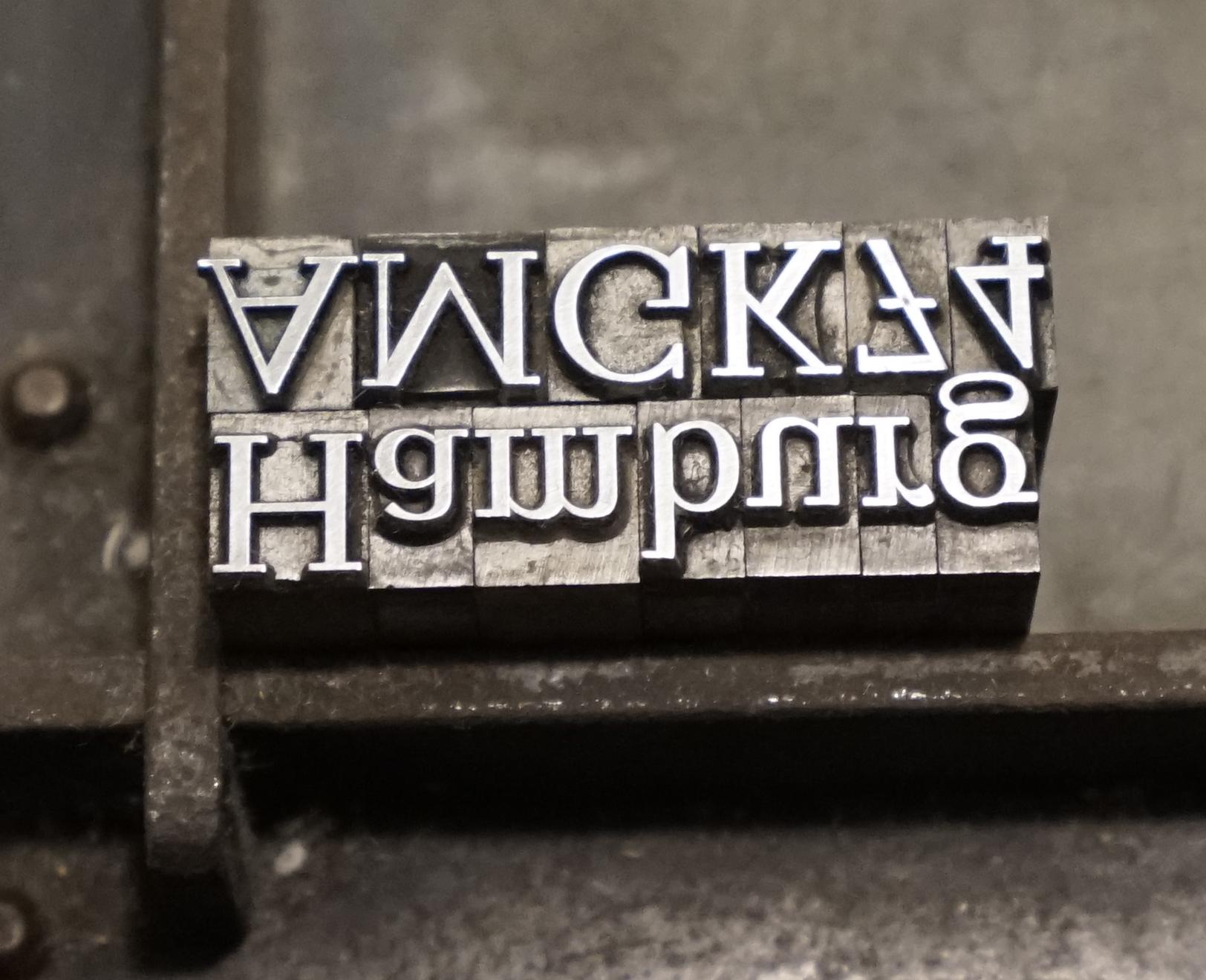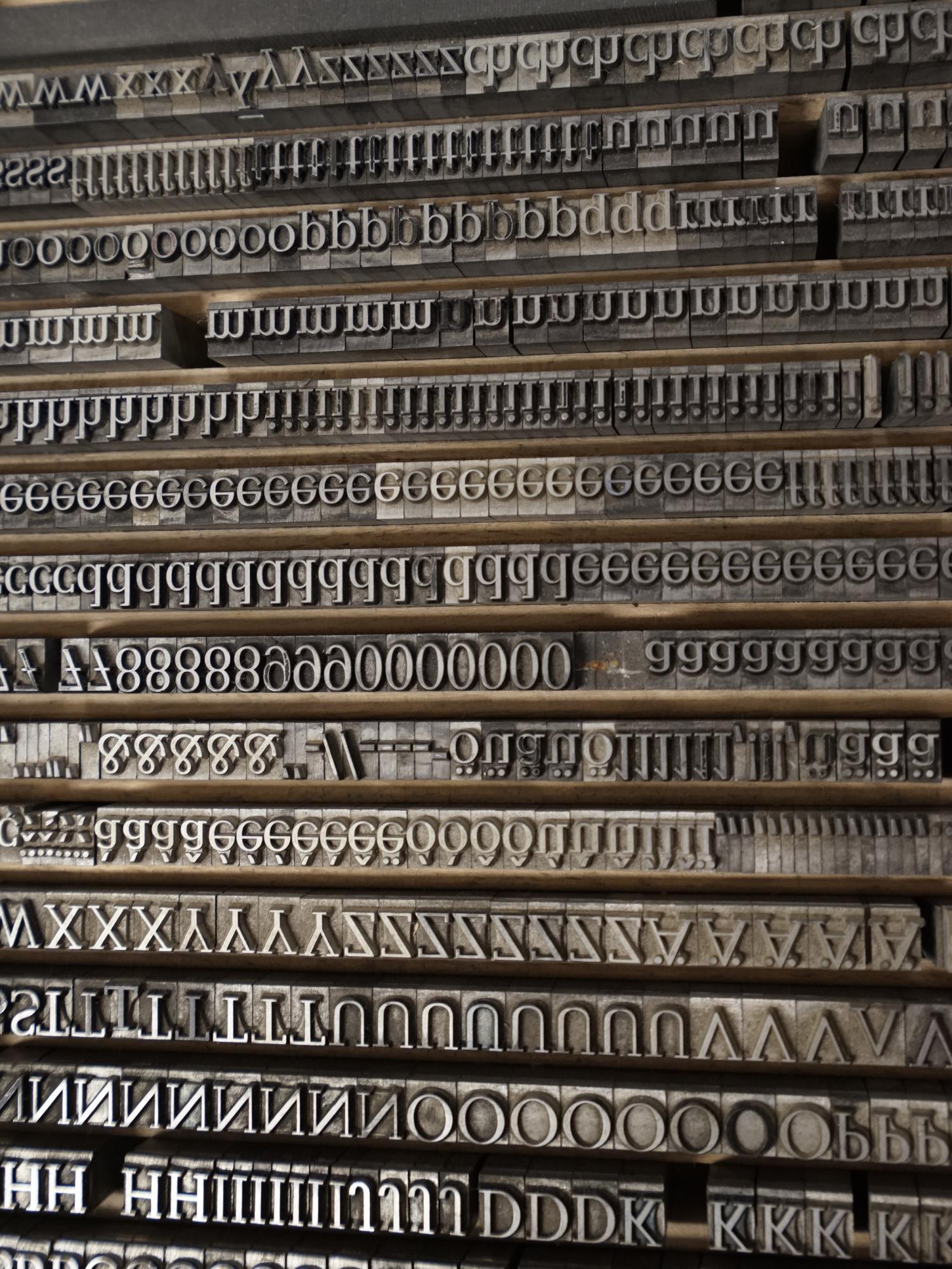
Unbekannte Bleischrift
bin mal wieder zu einer Schrift gekommen und kann sie trotz
intensiver Suche nicht identifizieren. Kann jemand helfen?
Das war auch mein erster Gedanke, kommt aber nicht hin.
Habe auch schon Erhardt, Melior, Ratio Latein und andere Kandidaten
überprüft. Trotzdem Danke für die Sonntagsarbeit  ; )
Manutius ist nahe dran (z.B. e), hat viel weniger Kontast, und das Versal K
ist auch anders. Seemann hat leider auch nicht geholfen. Die Einordnung
ist auch relativ schwer, denn der starke Kontrast deutet auf Klassizismus hin,
die fehlenden Enden in Tropfenform (e, r etc.) und die die Serifen im rechten
Winkel führen dann doch eher zur Egyptienne. Bastard!   LG ___ Peter
So, das Rätsel ist aufgelöst. Ralf, du hattes Recht: Candida. Irritierend ist,
dass diese Schrift überall mit einem zweistöckigen »g« angezeigt wird,
bei meiner Bleisatz-Schrift ist es dreistöckig. Zur endgültigen Klärung
hat eine Abbildung beim Bleisatzmagazin geführt. Dort ist eine 24 p
zum Verkauf, und die hat das dreistöckige »g«. Offenbar wurde diese
Änderung (Modernisierung?) bei der digitalen Umwandlung vollzogen.